Discover Japan(ディスカバージャパン) 2018年7月号
Discover Japan(ディスカバー・ジャパン)は、日本のモノ、コト、場所、人の魅力を再発見できる雑誌。日本古来から受け継がれる伝統的な文化として、陶磁器や染物、建築、食、祭りや風景が写真とともに解説される。
2018年6月6日に発売された「Discover Japan(ディスカバージャパン) 2018年7月号」では2018年の夏を満喫するために、創刊以来全国の名旅館や一流ホテル&リゾートを取材してきたディスカバージャパン編集部によるオススメの名宿とリゾートを紹介している。
秘密の夏宿
そろそろ夏休みのこの時期、夏を満喫するために絶対オススメの名宿とリゾートを紹介。話題のホテル&リゾートから老舗、知る人ぞ知る宿までバリエーションたっぷりに網羅して紹介いたします。たとえばいま続々オープンしている別荘気分が味わえる一棟スタイルの宿や、沖縄のリゾートの泊まり方指南、美味しい名宿の泊まり方といった、周辺情報を含めた具体的な宿の使い方についても紹介いたします。
2008年の名旅館特集を創刊号にスタートしたDiscover Japan。以来10 年間、全国の名旅館や一流ホテル&リゾートを取材しつづけてきた弊誌編集部が、本当におすすめしたい夏宿を特集いたします。
Discover Japan(ディスカバージャパン) 2018年7月号で「hibi×モリサワ 書体で感じる日々の香り。」情報が掲載
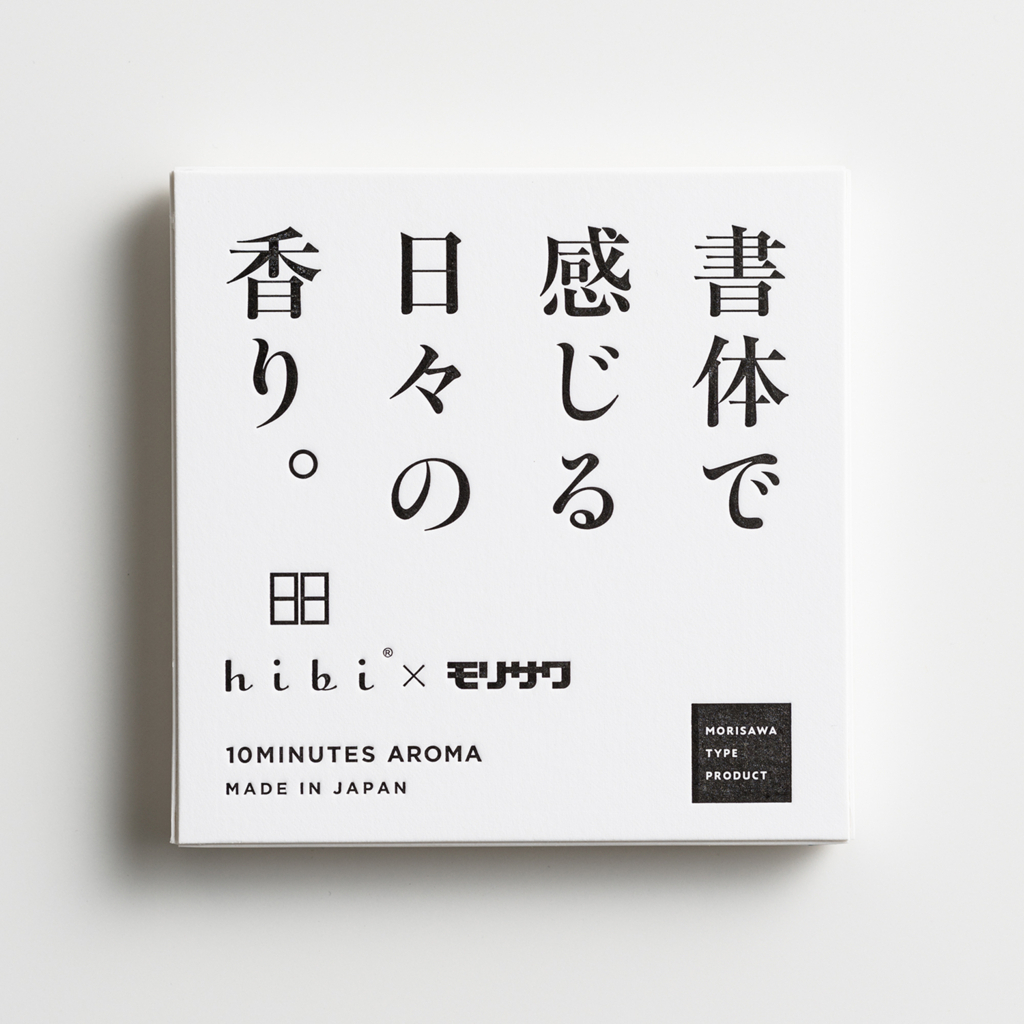
Discover Japan(ディスカバージャパン) 2018年7月号で、フォントベンダー「モリサワ」が自社ネットショップであるモリサワストアで販売しているオリジナルアロマスティック「hibi×モリサワ 書体で感じる日々の香り。」情報が掲載されている。
hibi×モリサワ 書体で感じる日々の香り。
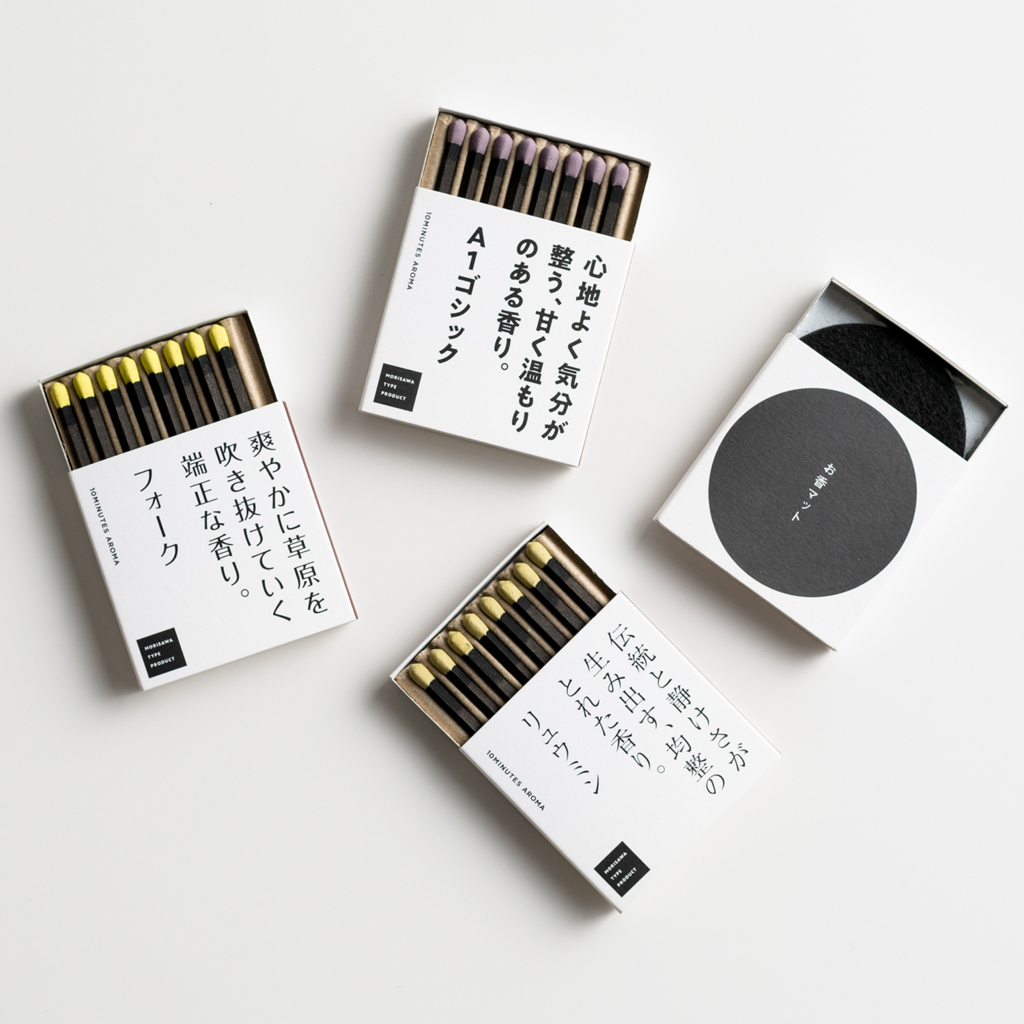
「hibi×モリサワ 書体で感じる日々の香り。」は、着火具がなくても手軽に使える全く新しいアロマスティック。
A1ゴシック、リュウミン、フォークといったモリサワを代表する3つの書体からインスパイアされた3種類の香りをセットにしやポケットサイズのアロマ。
A1ゴシック:ゼラニウム
心地よく気分が整う、甘く温もりのある香り
A1ゴシックはA1明朝の基本となる骨格を参照して作成された、オールドスタイルのゴシック体ファミリー。線画の交差部分の墨だまり表現や、エレメントの端々に僅かな角丸処理を加えることで、温もりのあるデザインに仕上げている。
リュウミン:檜
伝統と静けさが生み出す、均整のとれた香り
リュウミンは、森川龍文堂明朝体をベースに開発されたスタンダードな明朝体。金属活字に由来する彫刻刀の冴えを、左右のハライや点の形に活かしながらも、縦画・横画の先端やウロコにはやわらかさをもたせており、親しみやすい雰囲気になっている。
フォーク:レモングラス
爽やかに草原を吹き抜けていく端正な香り
フォークは、明朝体を思わせる細い横画と太い縦画で構成された、端正でスマートな雰囲気が特徴のモリサワのオリジナル書体。シンプルなカーブをもつ、奇をてらわない字形でありながら縦画と横画のコントラストが新鮮な印象を与える。
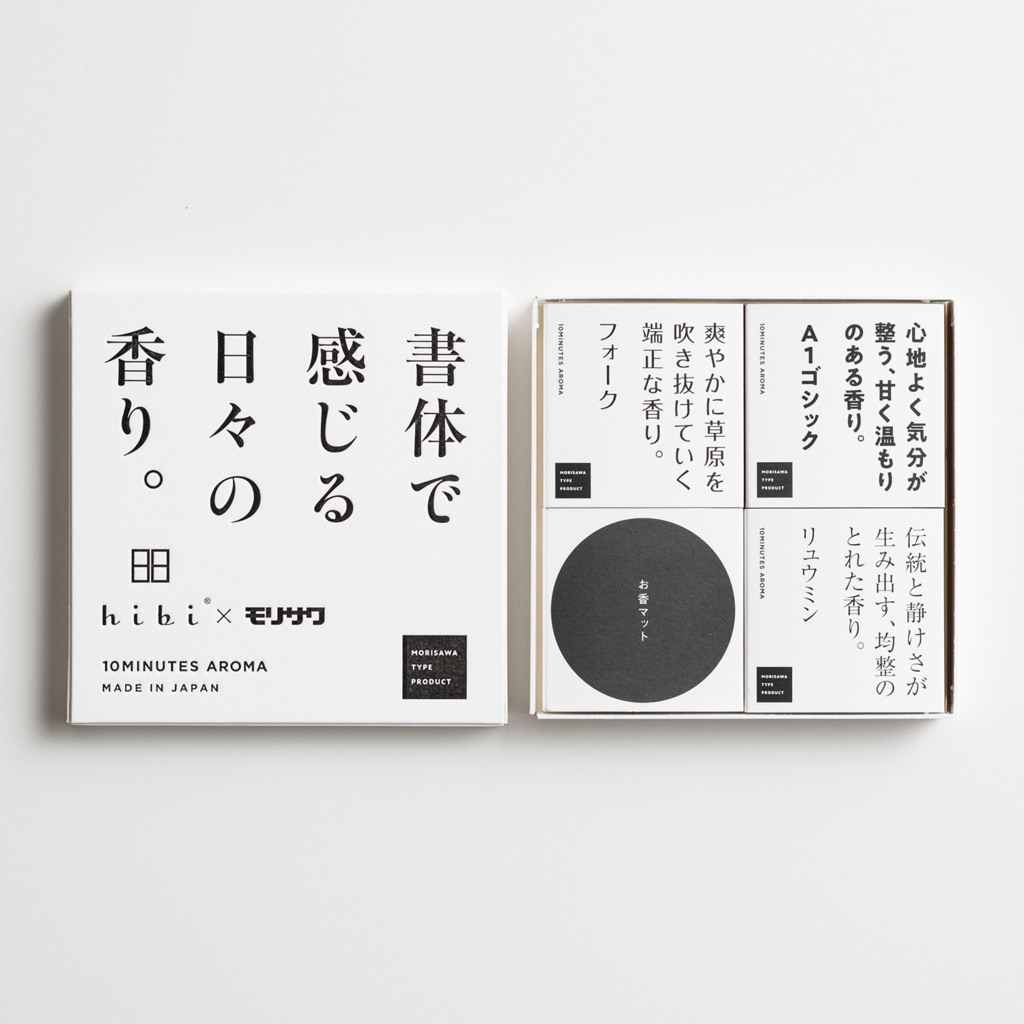
「hibi×モリサワ 書体で感じる日々の香り。」はモリサワの書体と日本のものづくりへのこだわりを融合させたオリジナルグッズを制作するプロジェクト「MORISAWA TYPE PRODUCT 」の第1弾アイテム。
開発は兵庫県播磨地方を拠点に1929年に創業したマッチ製造の長い歴史を持つ神戸マッチ株式会社と、1936年に淡路島で創業したお香製造会社、株式会社大発が共同開発したアロマスティック「hibi」とのコラボレーション。
「hibi×モリサワ 書体で感じる日々の香り。」は2018年4月10日のフォントの日に発売を開始した。